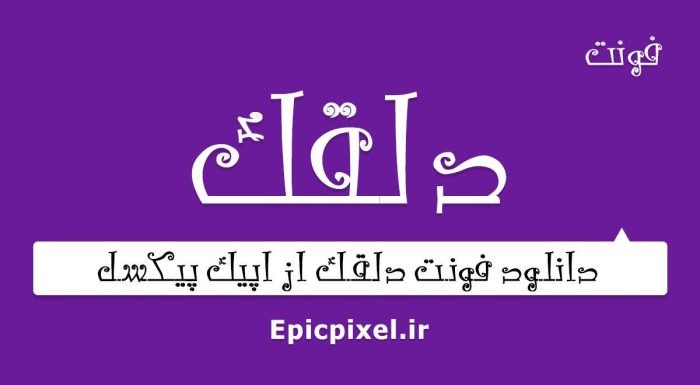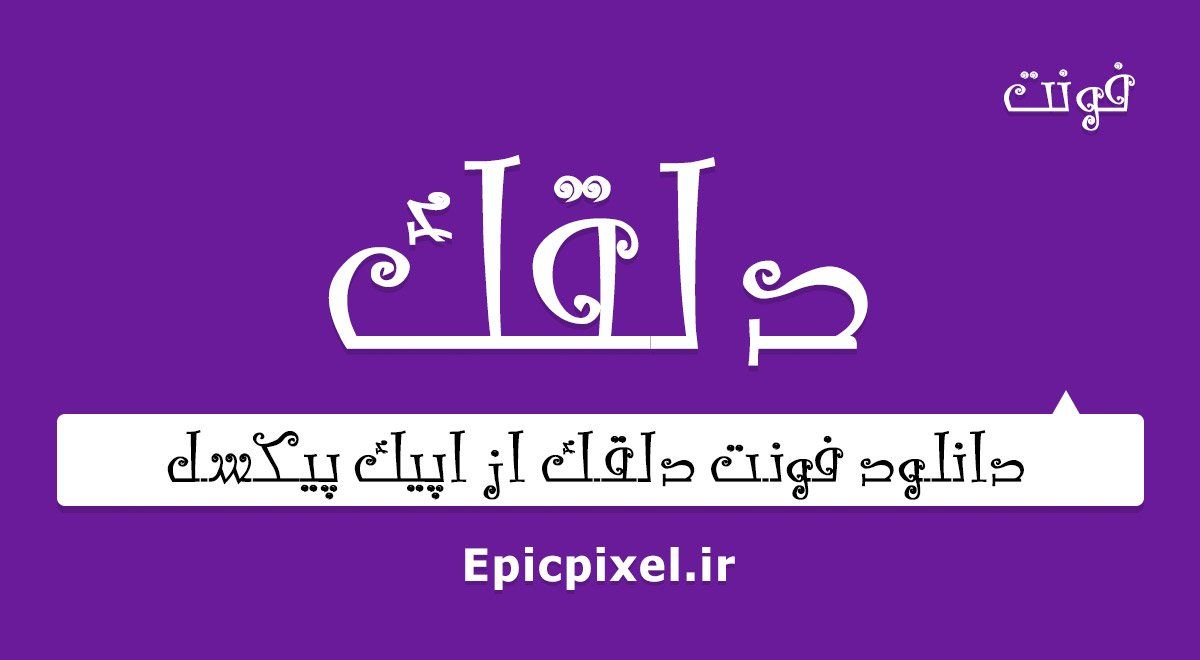
2 فونت دلقک فارسی
فونت دلقک فارسی، با طراحی خاص و منحصربه فردش، جلوه ای متفاوت و جذاب به نوشته های شما می بخشد. این فونت، با ساختار فانتزی و کمی اغراق آمیز در حروف، حسی از شادی و سرگرمی را القا می کند و برای استفاده در طراحی های گرافیکی، به ویژه مواردی که نیاز به جلب توجه و ایجاد فضایی دوستانه دارند، بسیار مناسب است.
اگر به دنبال فونتی هستید که نوشته هایتان را از حالت رسمی و خشک خارج کند و روحی تازه به آن ها ببخشد، فونت دلقک انتخابی ایده آل خواهد بود. این فونت، با وجود ظاهر خاصش، خوانایی مناسبی دارد و در اندازه های مختلف، به خوبی قابل استفاده است. از ویژگی های برجسته این فونت می توان به هماهنگی زیبای حروف با یکدیگر و ایجاد ترکیبی چشم نواز اشاره کرد که در هر طرحی، چه چاپی و چه دیجیتال، به خوبی خود را نشان می دهد.